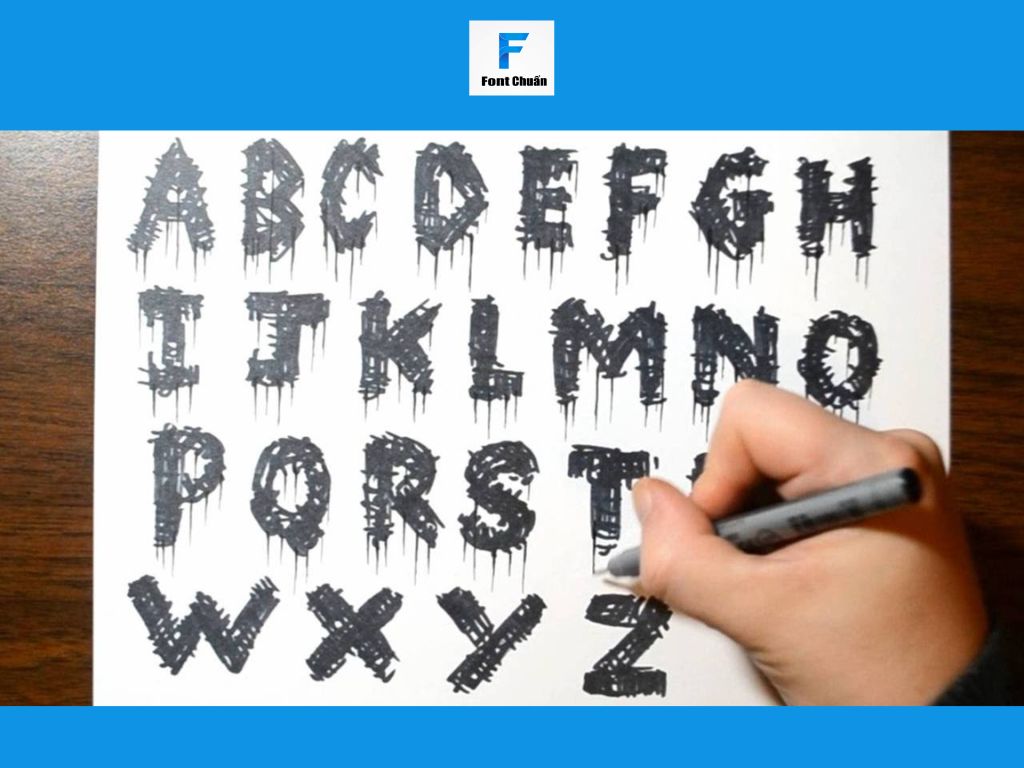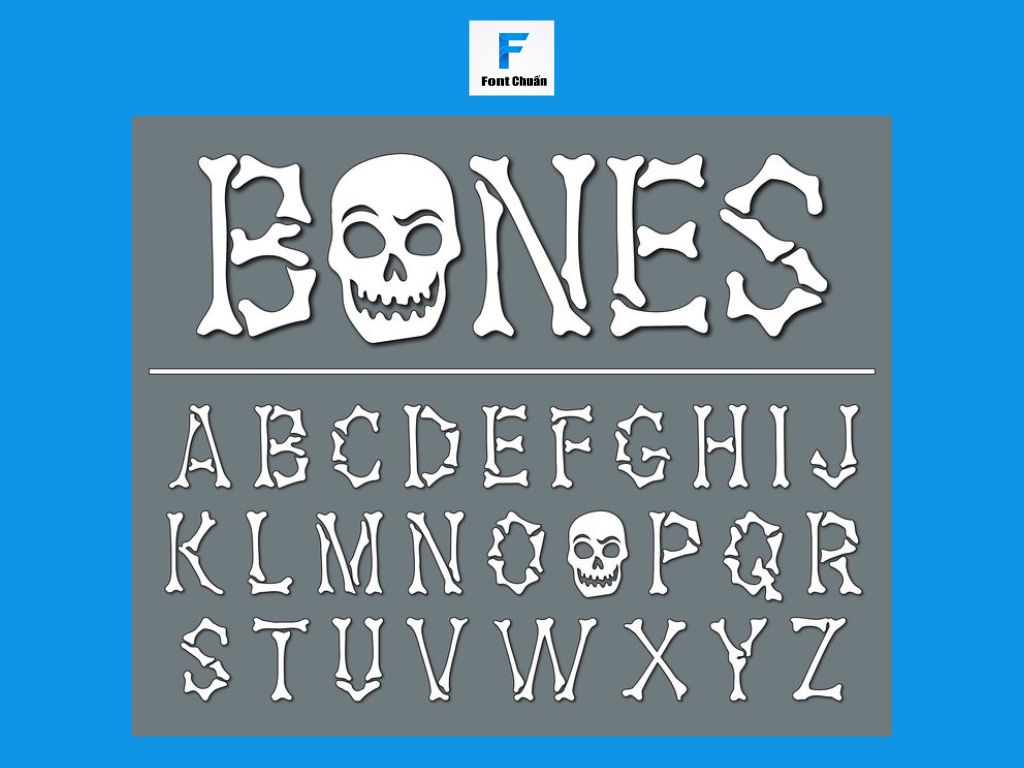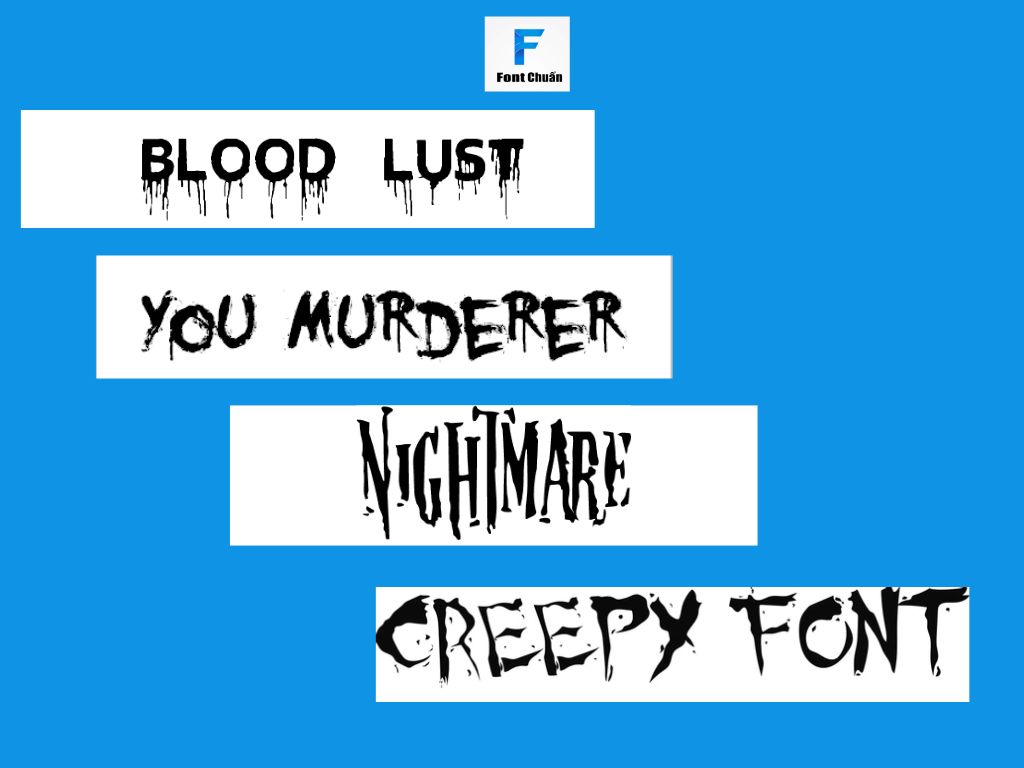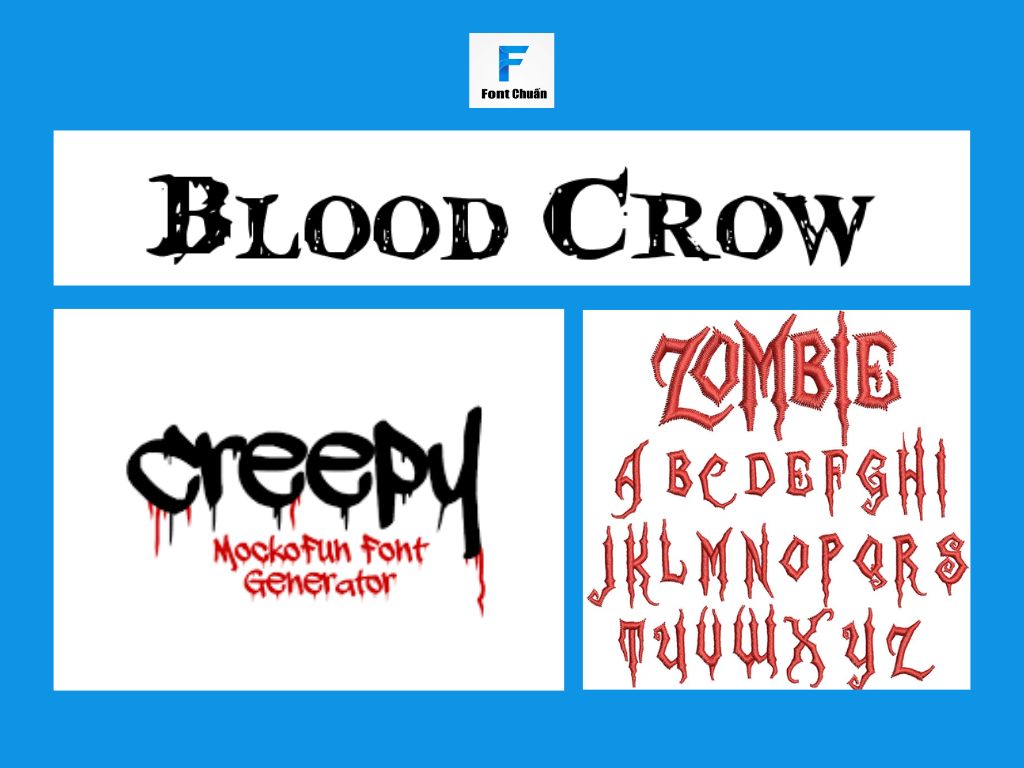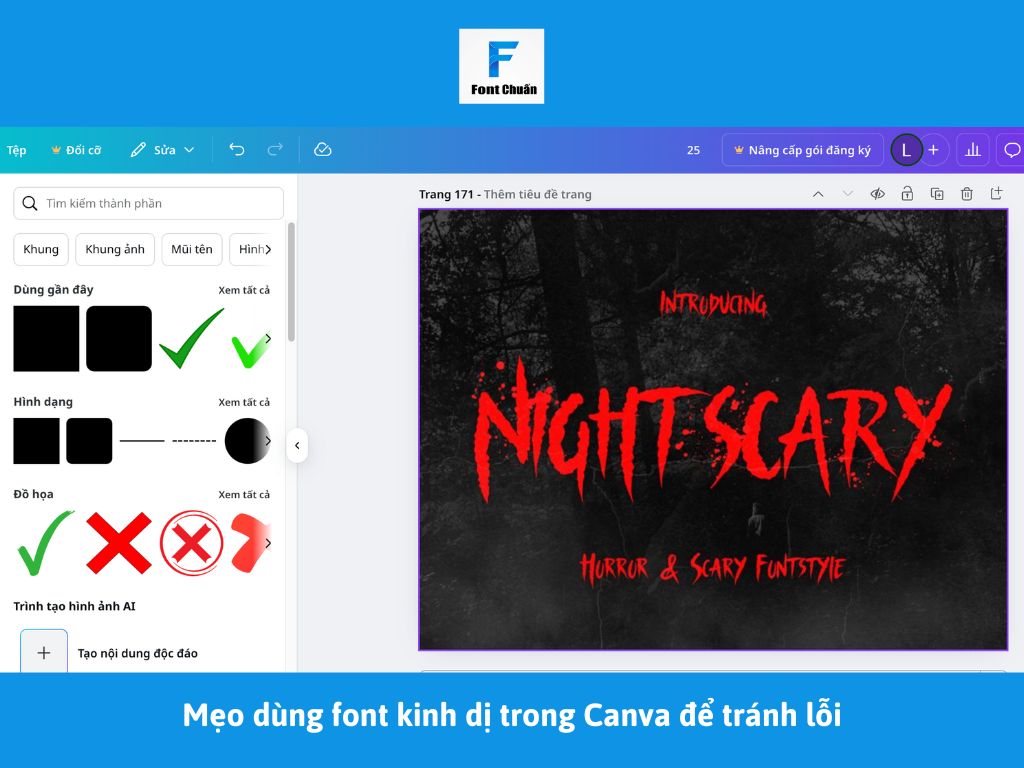
Ghim ngay 20+ Font kinh dị “đẹp lạnh gáy” dành cho designer
Bạn đang tìm kiếm những font chữ độc đáo để tạo hiệu ứng rùng rợn cho thiết kế poster, banner hay video Halloween? Font chữ kinh dị với phong cách máu chảy, bóng tối hay ma mị sẽ giúp tác phẩm của bạn “chuẩn vibe” đáng sợ. Danh sách 20+ font dưới đây chính là  “kho báu” cho các designer yêu thích sự kịch tính và ấn tượng.
Các phong cách font kinh dị phổ biến
Font kinh dị không chỉ có một kiểu duy nhất, mà được biến tấu đa dạng để phù hợp với từng bối cảnh khác nhau. Dưới đây là bốn phong cách đặc trưng thường gặp trong thiết kế:
Phong cách “máu nhỏ giọt”
Đây là kiểu font đặc trưng nhất khi nhắc đến kinh dị. Các nét chữ thường dày, thô và kéo dài xuống như những giọt máu đang rơi. Phong cách này thường thấy trong poster phim zombie, game bạo lực hoặc các thiết kế Halloween. Nó không chỉ gây cảm giác rùng rợn mà còn tạo ấn tượng mạnh ngay từ cái nhìn đầu tiên, khiến người xem liên tưởng đến sự chết chóc và nguy hiểm.
Phong cách “bút viết nguệch ngoạc”
Phong cách này mô phỏng những nét chữ viết tay vội vã, méo mó hoặc xiêu vẹo. Cảm giác mà nó mang lại giống như những dòng nhật ký bí ẩn, ghi chép của kẻ tâm thần hoặc lá thư để lại hiện trường vụ án. Font chữ kinh dị nguệch ngoạc thường được sử dụng trong poster phim kinh dị tâm lý hoặc thriller, giúp tăng cảm giác bất an và ám ảnh.
Phong cách “ma quái – hồn ma”
Ở phong cách này, các chữ cái thường có hiệu ứng mờ ảo, nhòe đi hoặc biến dạng, như thể đang tan biến vào bóng tối. Một số font còn được thiết kế theo kiểu “bóng đôi”, khiến chữ trông như có hồn ma lảng vảng xung quanh. Đây là lựa chọn lý tưởng cho thiết kế liên quan đến yếu tố siêu nhiên, linh hồn, haunted house hoặc các dự án mang hơi hướng huyền bí.
Phong cách “xương sọ & bóng tối”
Khác với các phong cách trên, kiểu font này thường có hình dáng mạnh mẽ, gai góc với chi tiết như xương, sọ, móng vuốt hoặc những đường cắt xé.
Nó thường được dùng trong các bìa album metal rock, logo tattoo hay game chiến đấu – kinh dị. Không chỉ gợi nỗi sợ, phong cách này còn thể hiện sự nổi loạn và cá tính mạnh mẽ, tạo cảm giác “dark” đúng nghĩa.
Tổng hợp 20+ Font chữ kinh dị cho thiết kế ma mị
Nếu bạn đang tìm kiếm nguồn cảm hứng để thiết kế poster phim, banner Halloween hay thumbnail YouTube về chủ đề rùng rợn, bộ sưu tập 20+ font kinh dị dưới đây sẽ giúp bạn tạo nên dấu ấn mạnh mẽ. Các font được chia thành hai nhóm: font quốc tế phổ biến và font đã được Việt hóa, phù hợp cho cả thiết kế tiếng Anh lẫn tiếng Việt.
Font kinh dị phổ biến
Blood Lust – nổi bật với hiệu ứng “máu chảy nhỏ giọt”, cực hợp cho các poster zombie hoặc tiêu đề phim kinh dị.
You Murderer – những nét chữ thô ráp, gai góc, mang đến cảm giác rùng rợn, thường được dùng trong thiết kế áp phích hoặc tiêu đề truyện tranh kinh dị.
Nightmare 5 – kiểu chữ đậm, biến dạng gợi cảm giác “ác mộng” bí ẩn, rất phù hợp cho game hoặc các dự án sáng tạo.
Creepy Font – phong cách cổ điển, dễ đọc, thường thấy trong các ấn phẩm mùa Halloween hay các thiết kế mang hơi hướng retro-horror.
Font chữ kinh dị Việt hóa
Nhu cầu sử dụng font kinh dị Việt hóa ngày càng cao vì nó giúp người thiết kế dễ dàng gõ tiếng Việt có dấu, tránh tình trạng lỗi font khó chịu.
Một số font Việt hóa nổi bật có thể tham khảo:
• Blood Crow Việt hóa – giữ nguyên tinh thần máu me rùng rợn, hỗ trợ đầy đủ Unicode.
• Creepy Horror Việt hóa – dễ dùng cho poster, banner hoặc các nội dung quảng bá sự kiện Halloween tại Việt Nam.
• Zombie Việt hóa – font block mạnh mẽ, ấn tượng, thích hợp cho game hoặc thiết kế tiêu đề video.
Lợi ích khi dùng font Việt hóa:
• Đảm bảo văn bản tiếng Việt hiển thị chính xác, không bị lỗi.
• Tiết kiệm thời gian chỉnh sửa, dễ kết hợp trong nhiều nền tảng thiết kế.
• Mang lại trải nghiệm thiết kế chuyên nghiệp, đồng bộ với nội dung bản địa.
Mẹo dùng font kinh dị trong Photoshop/Canva để tránh lỗi
Font chữ kinh dị thường có thiết kế độc đáo với nhiều chi tiết biến dạng, hiệu ứng máu nhỏ giọt hay nét nguệch ngoạc. Tuy nhiên, khi sử dụng trong Photoshop hoặc Canva, nếu không lưu ý, bạn có thể gặp các lỗi hiển thị hoặc font không hỗ trợ tiếng Việt. Dưới đây là một số mẹo giúp bạn tránh rắc rối khi thiết kế, tạo font chữ đẹp cho bản thiết kế của bạn: